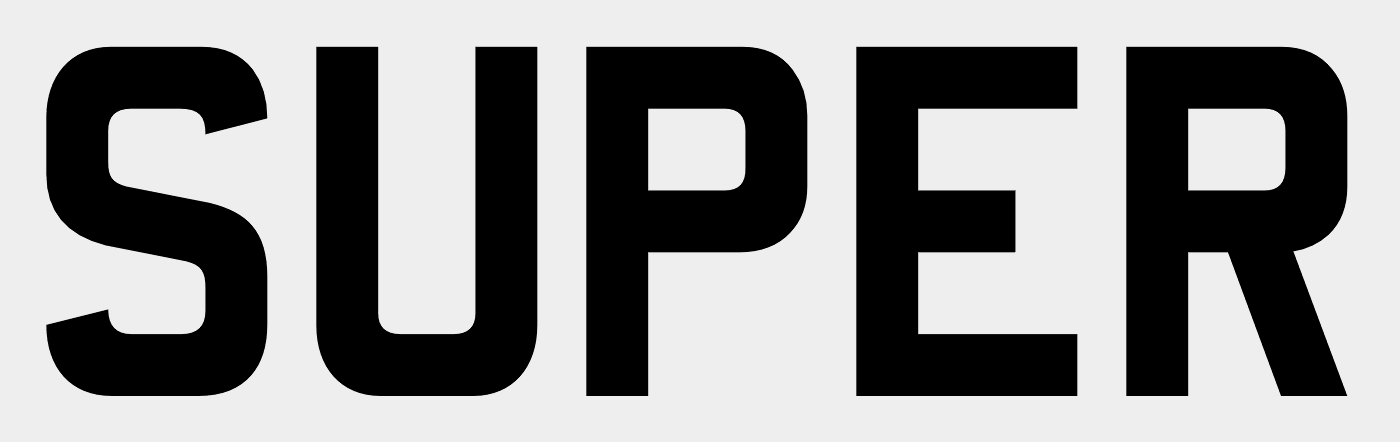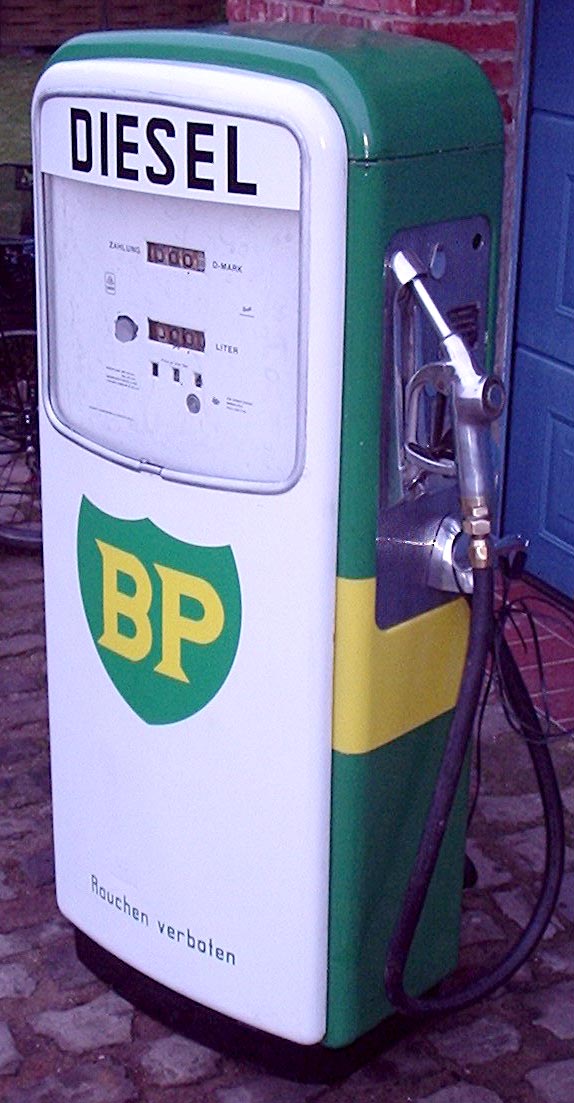
Suche Schriftart für beigefügtes Foto
ich suche die Schriftart für den Schriftzug "SUPER".
Die Schrift wurde wohl bei älteren, amerikanischen Tankstellen verwendet.
… und sogar ein wenig entzerren :-)
kann es sein, dass es sich hier um keine echte Satzschrift handelt? Möglicherweise sind das nach einem einfachen, geometrischen Prinzip gezeichnete Einzelbuchstaben. So haben die echten Schildermaler damals™ gearbeitet.
Ähnliche Prinzipien fand man bereits ab Mitte des 19ten Jahrhundert auf Grabsteinen, siehe Teuton von F, Storm, StormType  und möglicherweise Bank Gothic Morris Fuller Benton, Linotype. Hier die Quellen für die Angaben:
Bei der Bank Gothic sehe ich das aber als ungewiss an, da ich da nur diese eine Quelle kenne und keine weitere gefunden habe. Diese Gestaltungsregeln wurden dann später durch Bauhaus zur Modewelle in den 1930ern (siehe Beschreibungen zur Bank Gothic). Daher ist es durchaus möglich, dass die Vorlagen zu Fuß mundgeblasen wurden.
kann es sein, dass es sich hier um keine echte Satzschrift handelt?
Davon gehe ich mal aus. Das gesuchte Beispiel scheint eine Säule des Herstellers Gilbarco Schwelm aus den 60er-Jahren zu sein, der diese Form der Buchstaben eingesetzt hat.